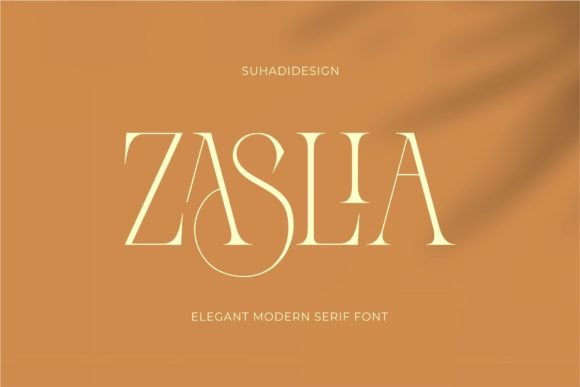
Zaslia
Zasliaのような高品質の素材をお探しの場合、このプレミアムパッケージはクリエイティブなプロジェクトに素晴らしい選択です。
精密に作られたZasliaは、クリーンなベクター、滑らかなタイポグラフィ、そして安心のための商用ライセンスを提供します。
POD(オンデマンド印刷)製品、結婚式の招待状、またはソーシャルメディアのグラフィックを作成している場合でも、Zasliaは理想的です。